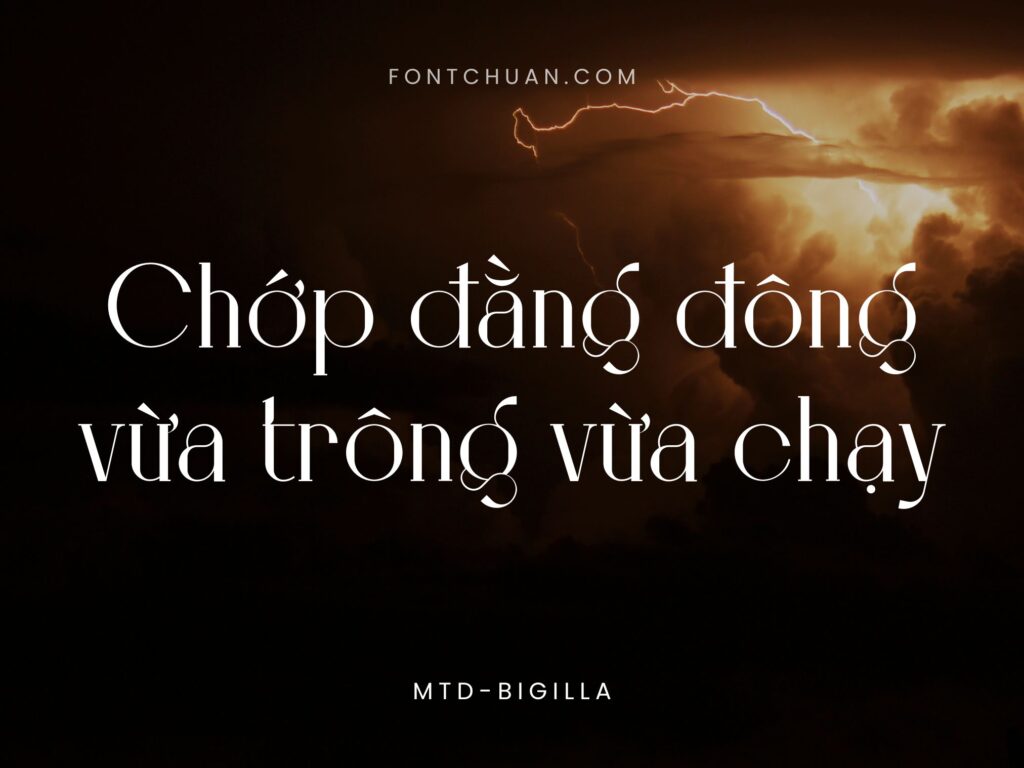
Font MTD Bigilla Việt Hóa
Font MTD Bigilla là một kiểu chữ serif hiển thị với độ tương phản cao, được thiết kế bởi Jérémie Gauthier và đã được Việt hóa bởi Mộc Hạ. Font này bao gồm hai trọng lượng (Regular và Bold) và tích hợp nhiều ligatures cùng các ký tự thay thế, hỗ trợ đa ngôn ngữ, bao gồm tiếng Việt. Đây là một trong những phông chữ được cộng đồng thiết kế đánh giá cao và sử dụng trong nhiều dự án sáng tạo, đáp ứng nhu cầu đa dạng của người dùng.
MTD Bigilla nổi bật với các đường nét thanh lịch và tinh tế, mang đến cảm giác sang trọng và hiện đại. Font rất phù hợp cho các thiết kế logo, tiêu đề, bao bì sản phẩm, thiệp mời và các ấn phẩm đòi hỏi sự tinh tế và nghệ thuật. Các ngành nghề phù hợp bao gồm quảng cáo, giáo dục, công nghệ, thiệp cưới và ảnh cưới. Font này cũng lý tưởng cho các sự kiện như Tết, Giáng sinh, Valentine và các lễ hội khác.